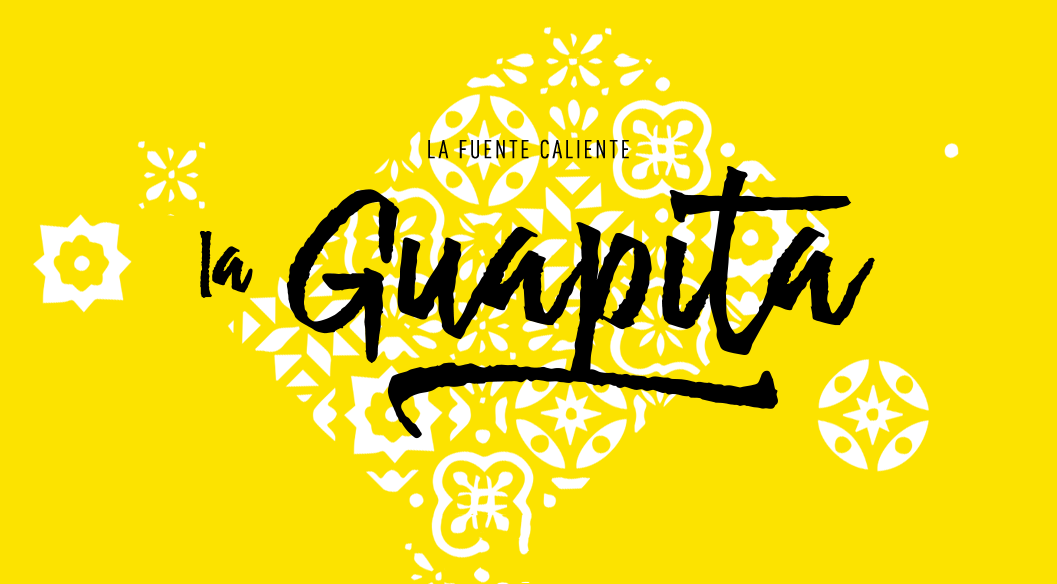
La Guapita Font – Download Grátis
Esta fonte chamada ‘La Guapita Font’ é perfeita para aqueles que adoram personalizar textos de maneira elegante. Criada pelo designer StereoType, ela pertence à categoria de Brush Fonts e traz uma mistura única e envolvente. Ideal tanto para quem deseja criar um estilo único no seu design pessoal como para designers profissionais que buscam flexibilidade na criação de layouts comerciais. Completamente personalizável, a versão comercial da font inclui uma vasta variedade de alternativas de gírias, ligaturas contextualas e soblinhados. Estes detalhes adicionam uma profundidade única ao texto, permitindo que você crie seus próprios estilos únicos, seja em design gráfico, ilustrações digitais ou até mesmo aplicativos móveis. Como um designer criativo, StereoType fez deste font verdadeiro uma obra de arte. Ele destaca seu amor pela arte e sua paixão pelo design ao criar algo que vai muito além das simples características gerais de uma fonte – é uma ferramenta para expressar o seu estilo pessoal em cada projeto. Se você é um profissional do design buscando dar vida a seus projetos, ou se ama a ideia de explorar novas formas e texturas no texto, ‘La Guapita Font’ será definitivamente uma escolha incrível. Não hesite, experimente – você vai adorar usá-la!